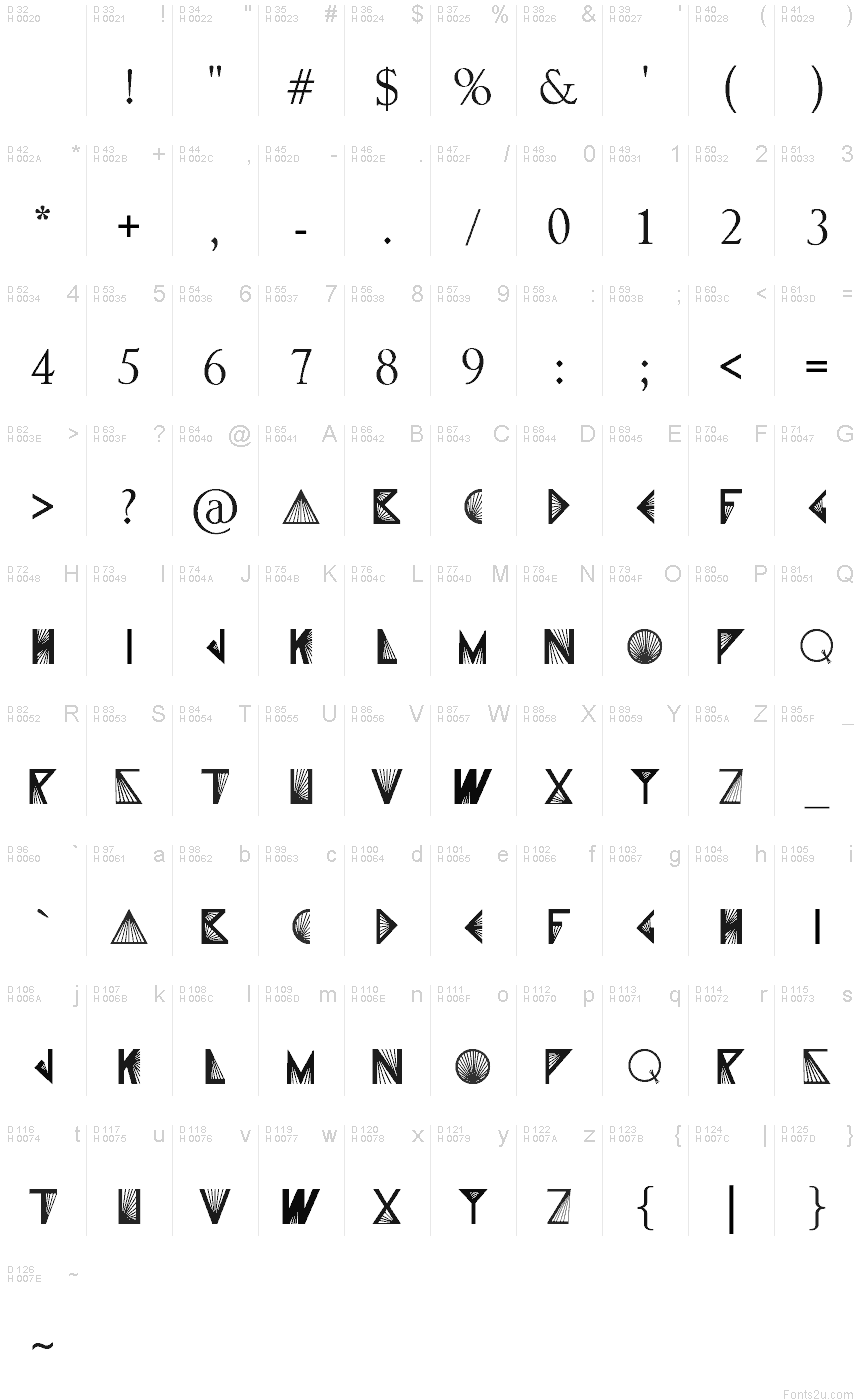
X-PRISM
Inspirado no logotipo da turn da cantora Katy Perry (Prismatic). As restantes letras que no compem o ttulo da tour foram criadas e editadas por mim. // Inspired on the "PRISMATIC Tour" (from Katy Perry) logo. The other words are created by myself.